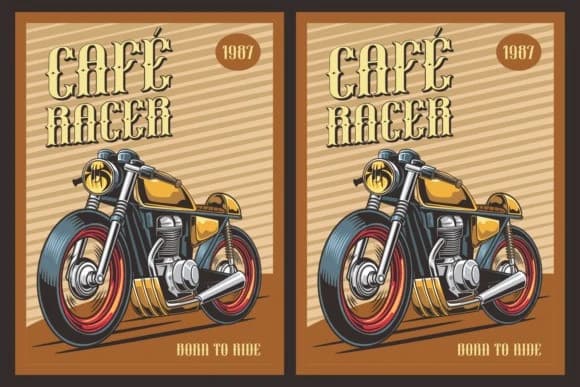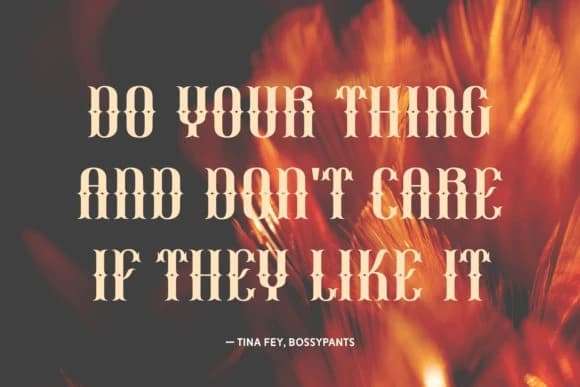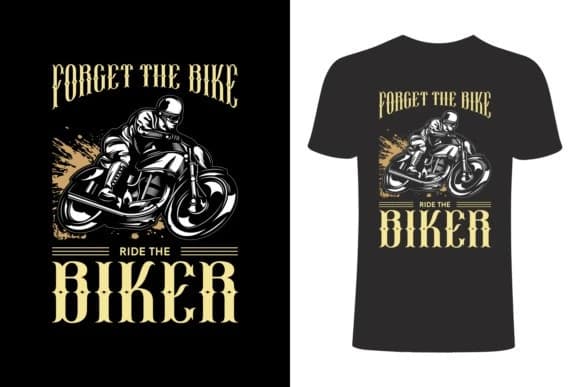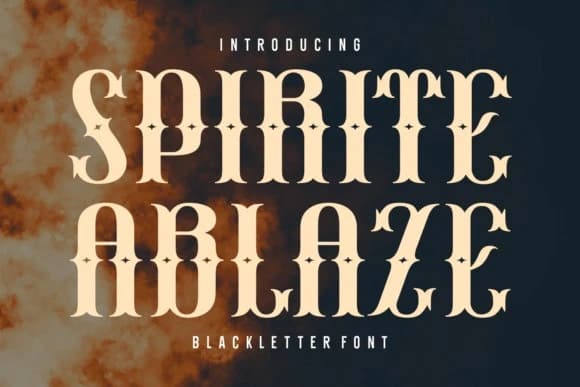
Spirite Ablaze Font, kalın ve ağır harfli bir blackletter fontudur. Projelerinize güvenle ekleyin; sonuçları çok beğeneceksiniz. Bu font PUA kodlu olduğundan, tüm gliflere ve swash'lara kolaylıkla erişebilirsiniz!
Spirite Ablaze Font, kalın ve ağır hatlı bir blackletter yazı tipi̇dirdir. Projelerinize güvenle ekleyin; sonuçları beğeneceksiniz. Bu yazı tipi PUA kodlu olup tüm gliflere ve swash'lara kolayca erişebileceğiniz anlamına gelir!